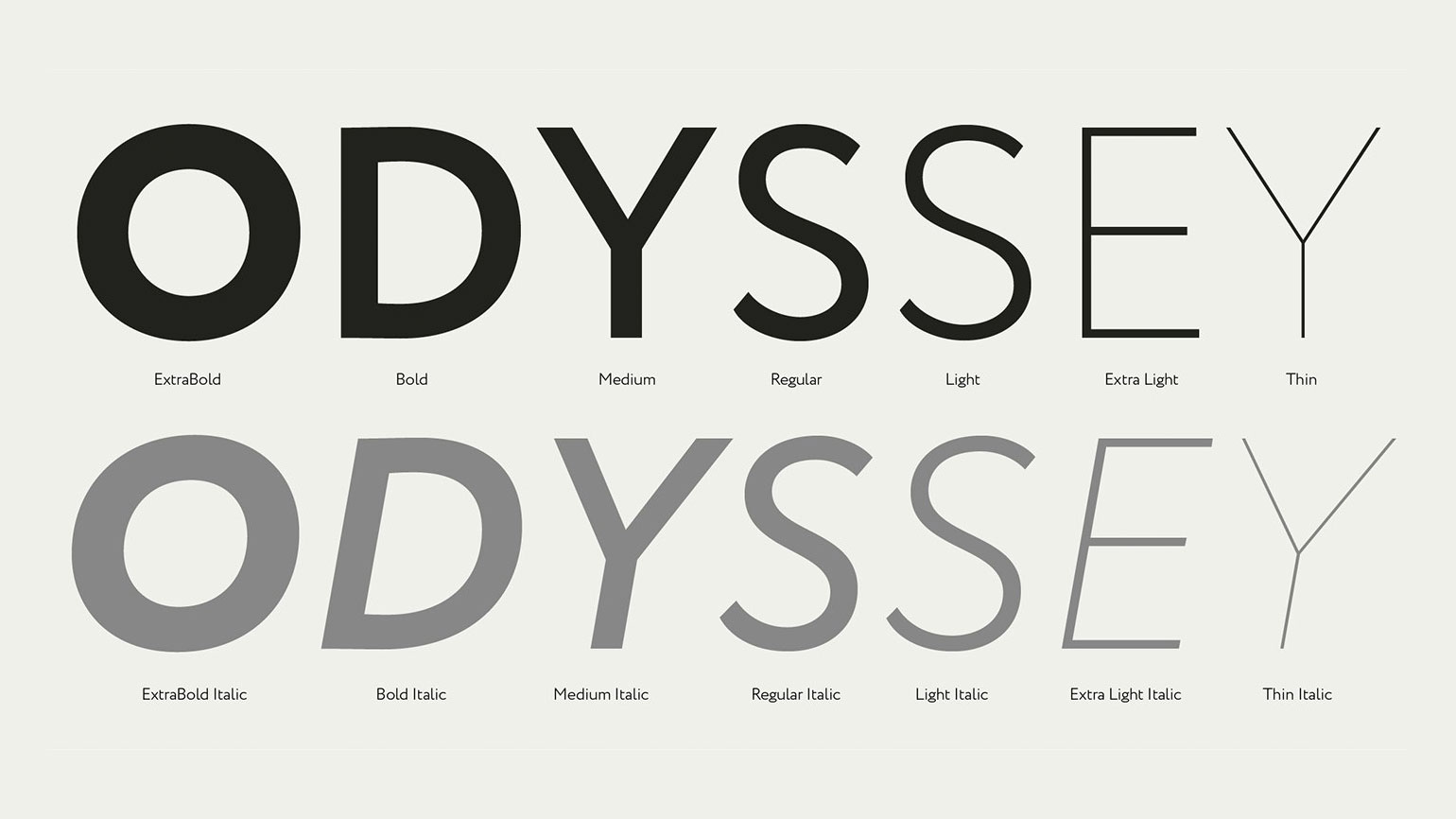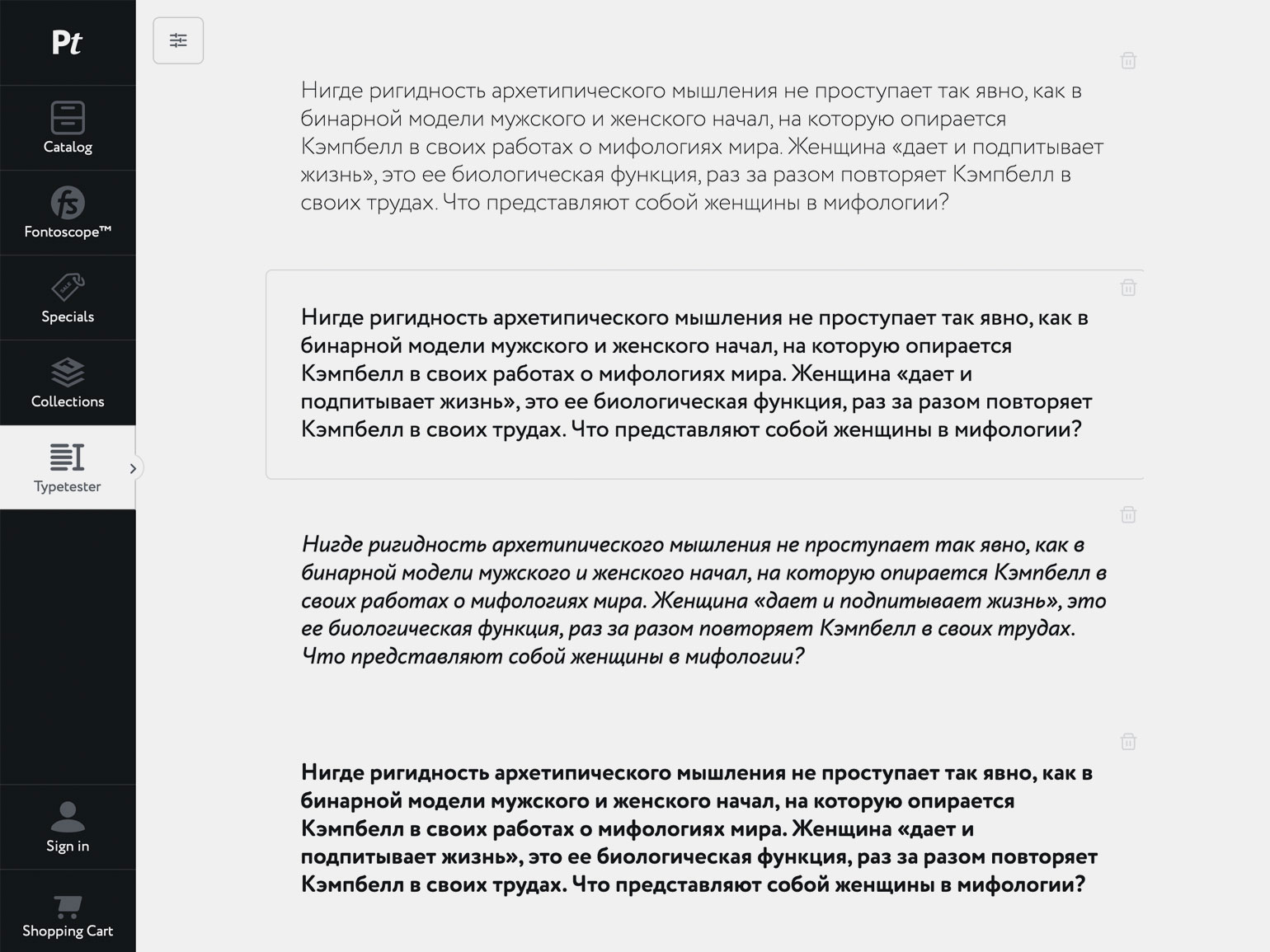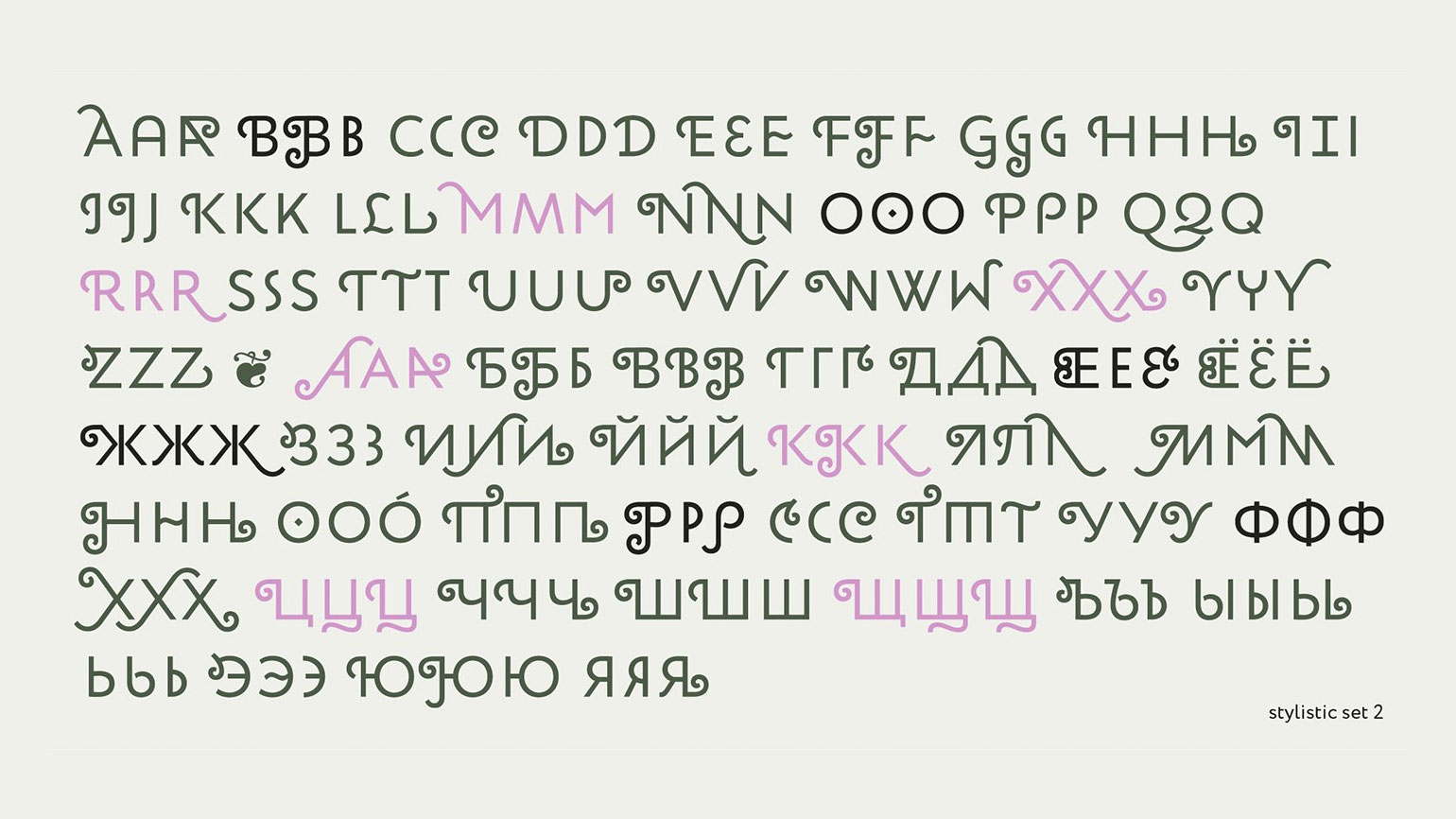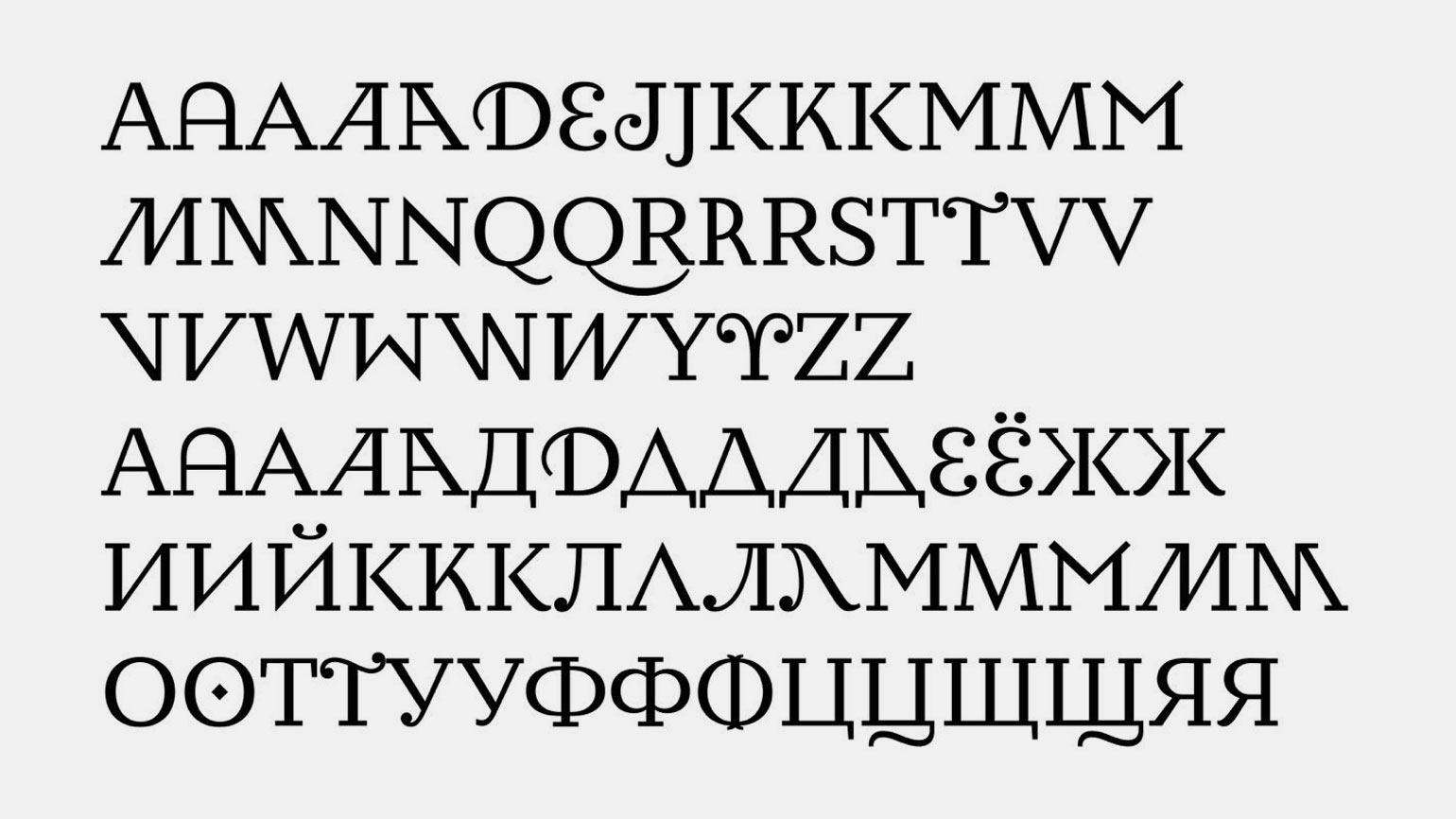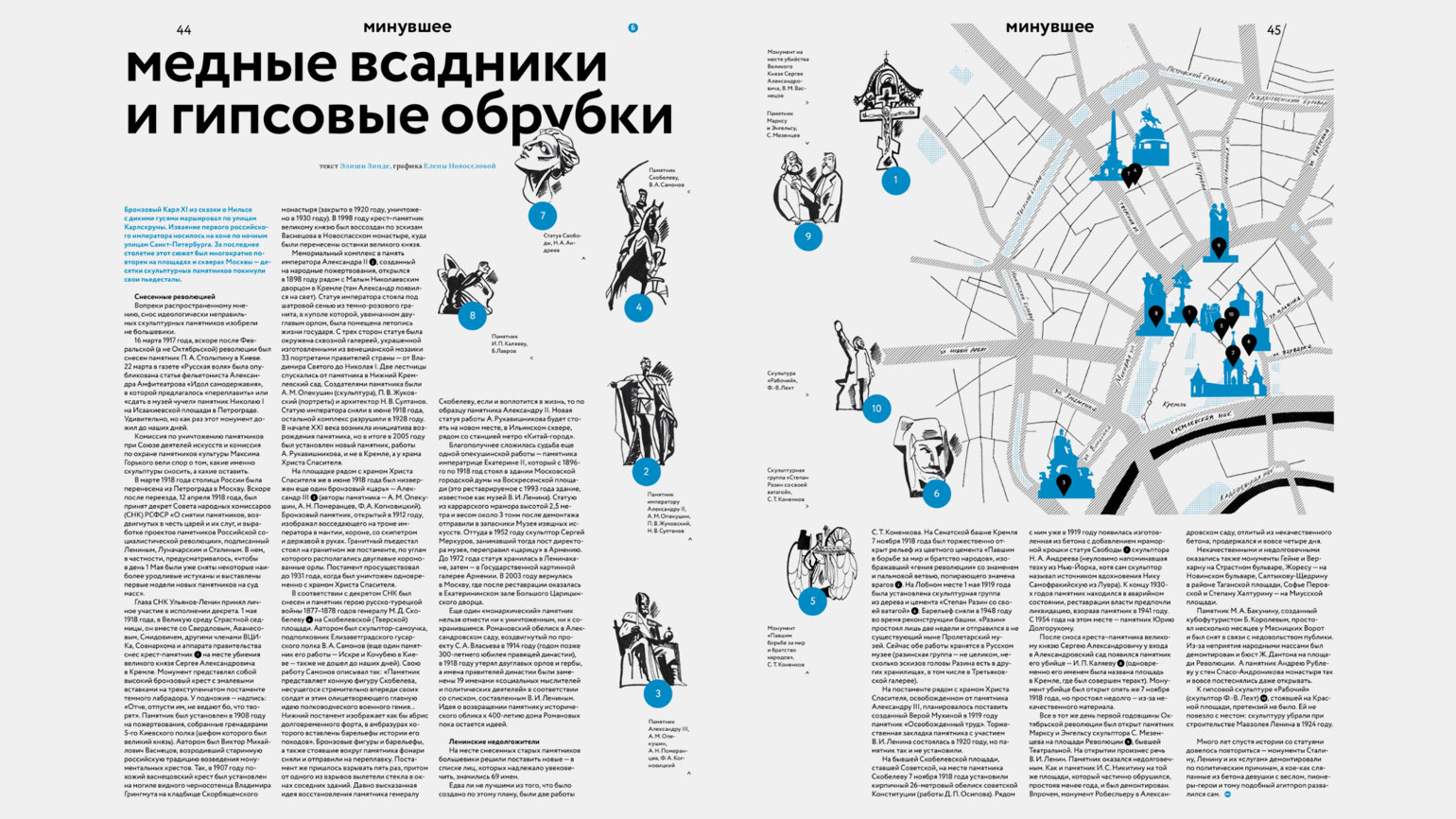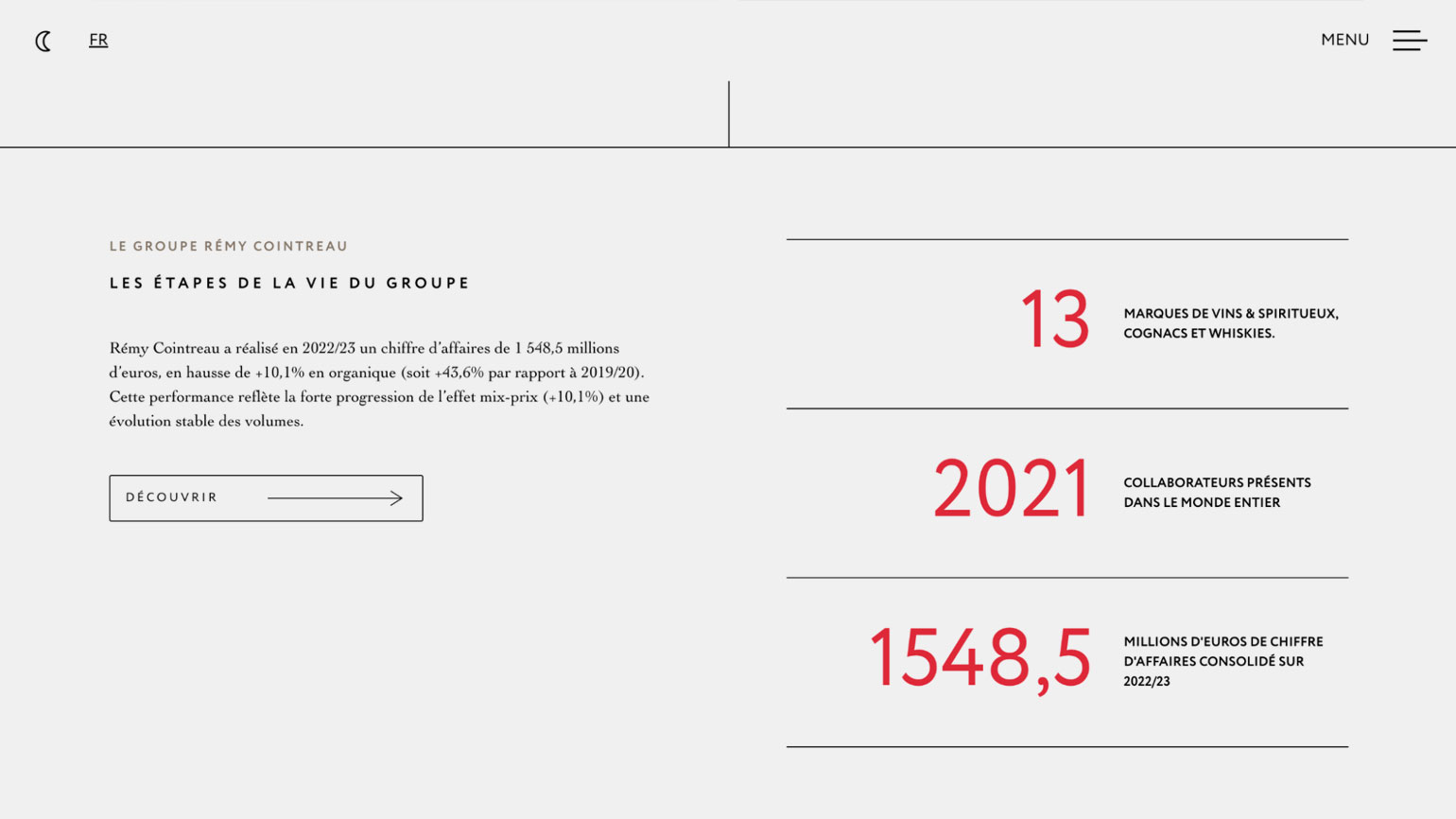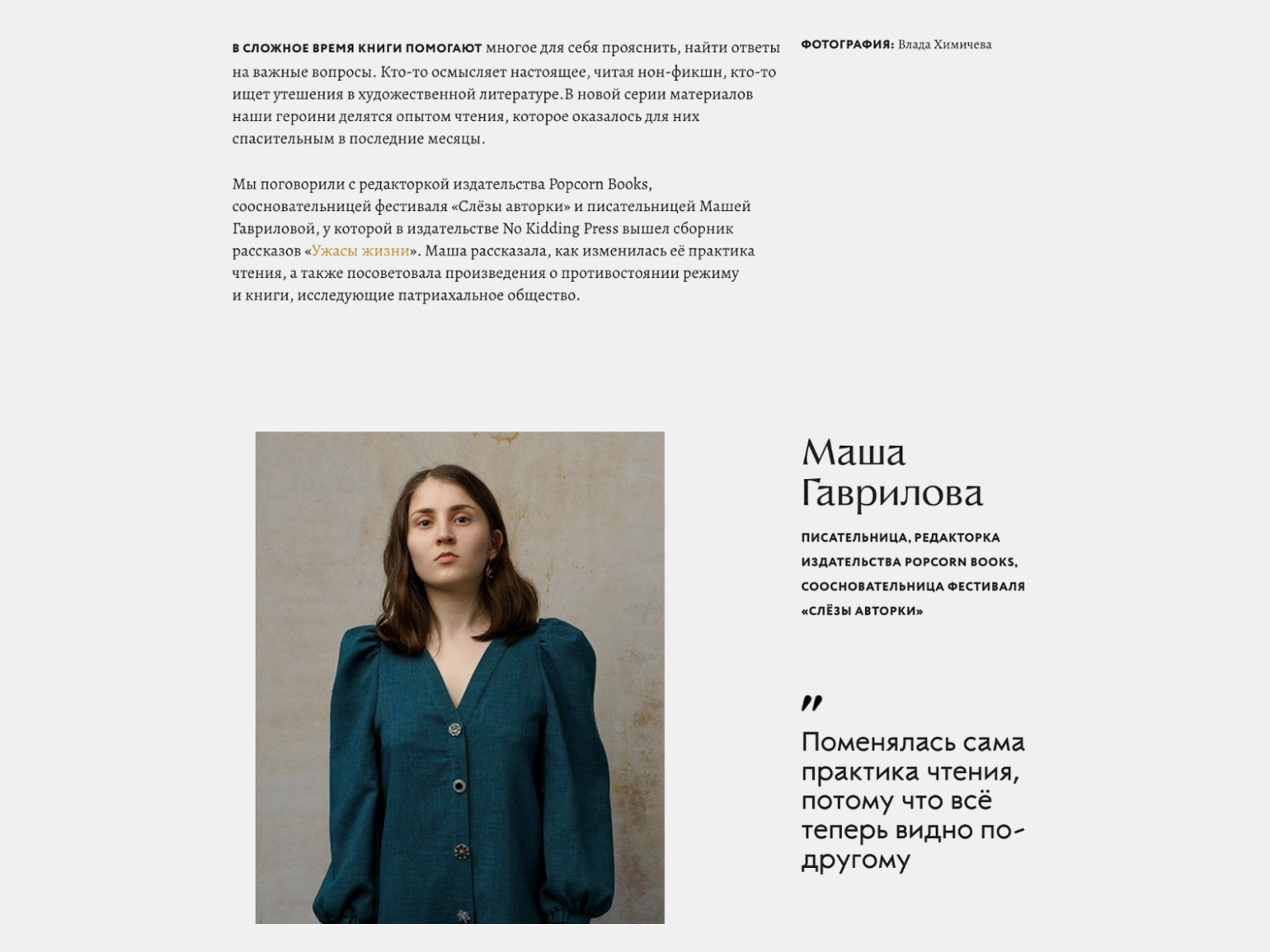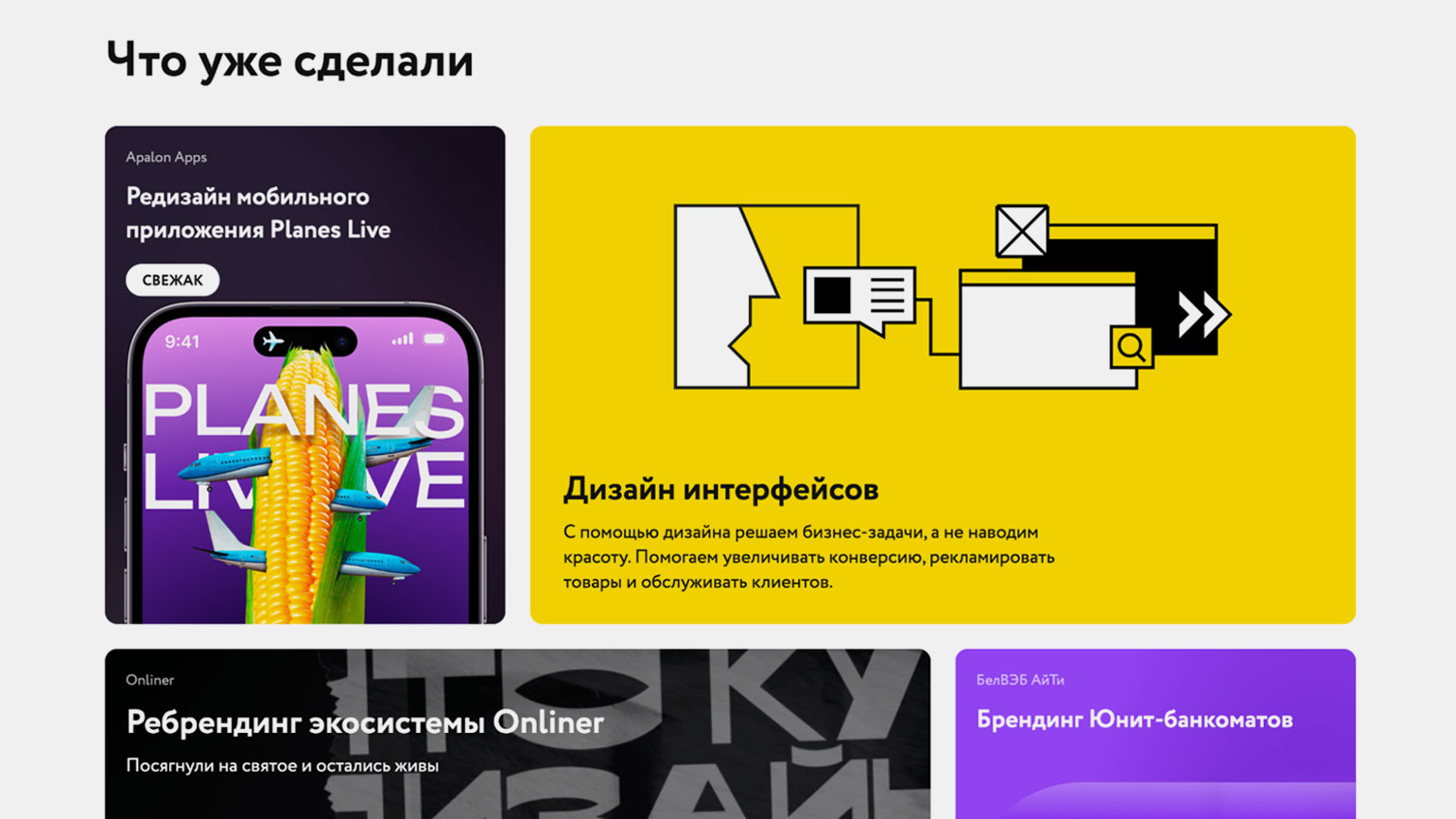
Circe: где используют и с чем сочетают
Рассказываем о шрифте с кириллицей и секретами.
Circe — один из популярных шрифтов. Мы решили разобраться не только в его графике, но и узнать, какой символизм есть в названии. Плюс — показать примеры современного дизайна с ним.
Circe: что это за шрифт
В 2010 году дизайнер студии Paratype Александра Королькова решила создать новый тиражный шрифт — «геометрический гротеск с человеческим лицом и с финтифлюшками» и, конечно, кириллицей высокого качества. Он должен был обязательно подходить для набора больших текстов и при этом иметь альтернативные варианты знаков, причём с декором исключительной красоты.
Уже в 2011 году вышла первая версия Circe, в которой был впечатляющий знаковый состав — больше 2500 глифов на каждое из шести прямых начертаний.
Сейчас Circe — это:
- Семь прямых начертаний насыщенностью от Thin до Extra Bold и семь соответствующих курсивов.
- Базовая, расширенная, историческая, азиатская кириллица плюс кириллические гласные с акутами.
- Западная и центральноевропейская латиница.
- Дроби и степени.
- Распространённые специальные знаки и редкие символы: карточные масти, три вида указующего перста (такие знаки присутствовали во многих доцифровых шрифтах) и другие интересные элементы.
- Стилистические сеты с альтернативными знаками, которые могут кардинально изменить оформление текста.
Кроме того, за годы у Circe появились «родственники» — брусковая Circe Slab, контрастный гротеск Circe Contrast (сейчас на этапе бета-версии) и скруглённый дружелюбный Circe Rounded.
— Circe подходит для детских книг и учебных изданий, потому что это не совсем геометрический гротеск, это гибрид геометрии и гуманизма. Везде, где в дизайне шрифта есть развилка — выбрать геометрическую или гуманистическую форму, — я выбирала гуманистическую. Поэтому формально его можно записать в геометрические гротески, а на деле он текстовый и человечный.
И это всё-таки скорее текстовый шрифт. Насколько я увидела за прошедшие годы, яркие макеты с ним делают очень редко. В основном Circe берут для текста, максимум — подзаголовков.
Проект, который меня как автора шрифта сильно порадовал почти сразу после релиза, — это журнал «Московское наследие», который делали ребята из «Щуки» в те времена, когда они занимались многостраничниками, а не айдентикой. А самым удивительным проектом была навигация в Центральном детском магазине на Лубянке, в которой использовали примерно все буквы с завитушками сразу. После этого я поняла, что в следующих шрифтах их в таком количестве делать не надо :)
У дизайнера шрифта могут быть любимые знаки, классический пример — Эрик Шпикерманн, который в интервью говорил, что любит цифры. Я не готова рассуждать в духе «буква а и цифра 2 мне особенно удались», но у меня сложился набор любимых альтернативных знаков, которые перекочевали сначала в Circe Slab, а потом в Circe Contrast — наверное, их можно считать визитной карточкой большой семьи «Цирцей».
Разрабатывала Circe Александра Королькова в формате «реалити»: она показывала весь процесс и подробно рассказывала о каждом этапе. Этот дизайн-дневник можно прочитать здесь.
Название Circe — английский вариант имени Цирцея. Это женское имя — метафора двойственности в природе шрифта: основной набор графически спокойный, альтернативный — сложен.
«По замыслу автора изобилие форм знаков, с одной стороны, дарит дизайнеру невиданную свободу, с другой стороны — может завести его в опасные дебри, словно спутников Одиссея на остров колдуньи Цирцеи».
Из интервью Александры Корольковой для журнала «Шрифт»
Цирцея — героиня мифов Древней Греции и гомеровского эпоса, колдунья и знахарка, дочь бога Солнца и океаниды, превратившая моряков Одиссея в свиней. У этого образа глубокие корни, поэтому мы попросили эксперта по мифам и языку рассказать о его значении и символике.
— Графика шрифта Circe напоминает греческий меандр, а тот, в свою очередь, восходит к лабиринту — важному для человечества символу бессмертия.
Цирцею можно считать архетипической фигурой — у неё божественное происхождение. Любой архетип биполярен, и Цирцея не исключение. С одной стороны, она врачевательница и ведьма, знающая секреты разных целебных трав, а с другой — мстительная особа, способная изменять облик других людей и нимф. Кроме того, она поделилась некоторыми своими ценными знаниями с Одиссеем.
У самого имени Цирцея двойная этимология. По одной версии это производное от cirke, «круг», а другая предполагает, что её имя родственно ястребу-перепелятнику.
Если брать версию про круг, то это, с одной стороны, отсылка к отцу Цирцеи Гелиосу, богу солнца, а с другой — к тому, что она воплощала Великую мать в её аспекте повелительницы зверей.
Я бы не сказала, что этот образ популярен в искусстве, но тем не менее интерес к ней есть, и Цирцея известна даже больше, чем Калипсо. Например, Мадлен Миллер посвятила целый роман деконструкции мифа о Цирцее, у Кортасара есть рассказ «Цирцея». В массовом дизайне я встречала её на аркане Таро в колоде Dark Goddess Tarot.
Аналоги Circe
Графика и идея Circe уникальны. Однако если этот шрифт не подходит, но для дизайна нужно что-то условно подобное, можно посмотреть на альтернативы: